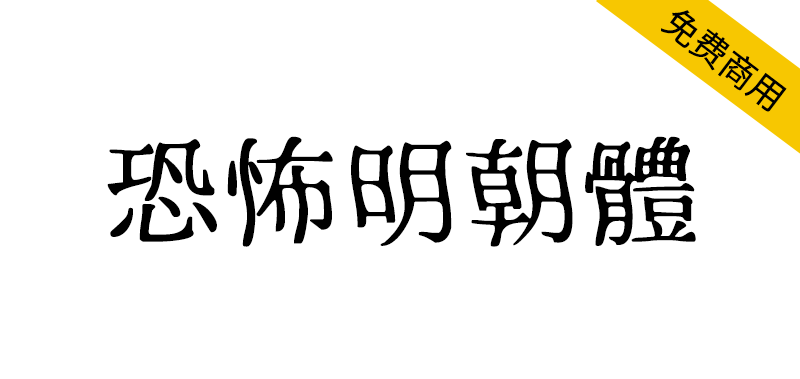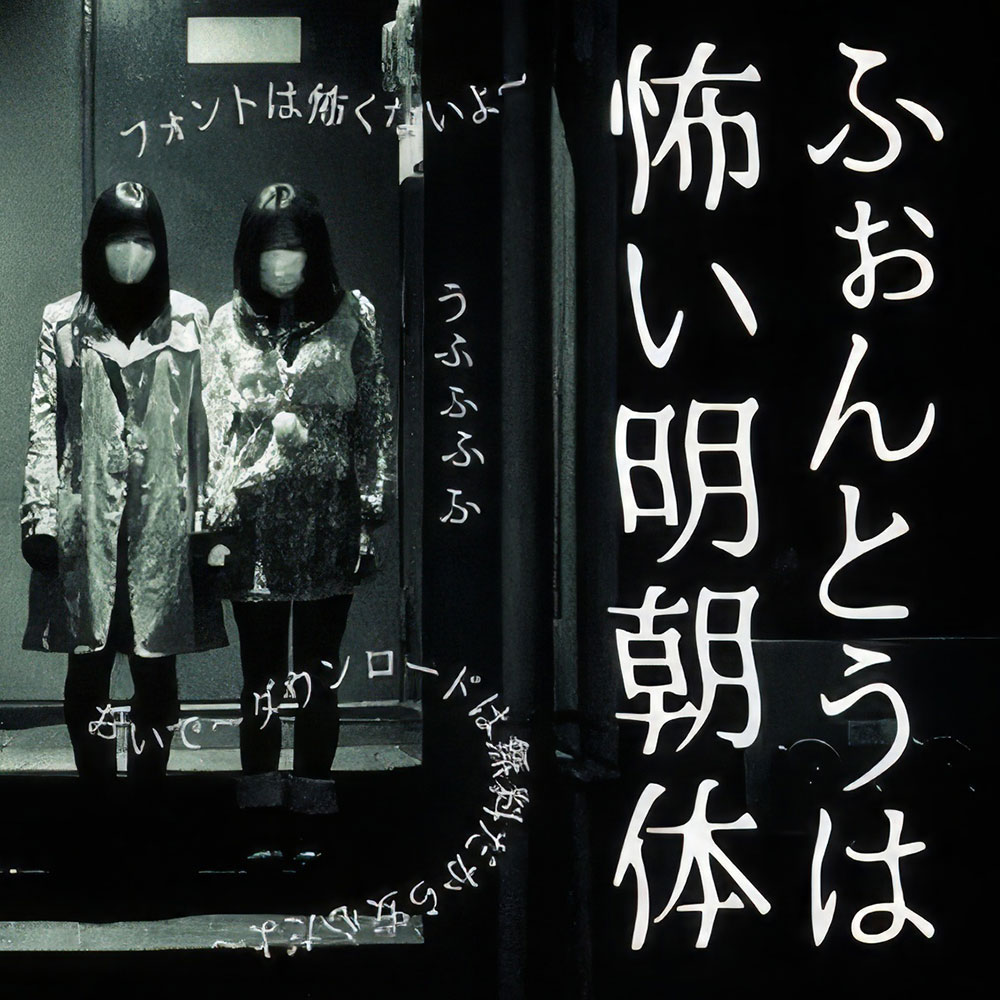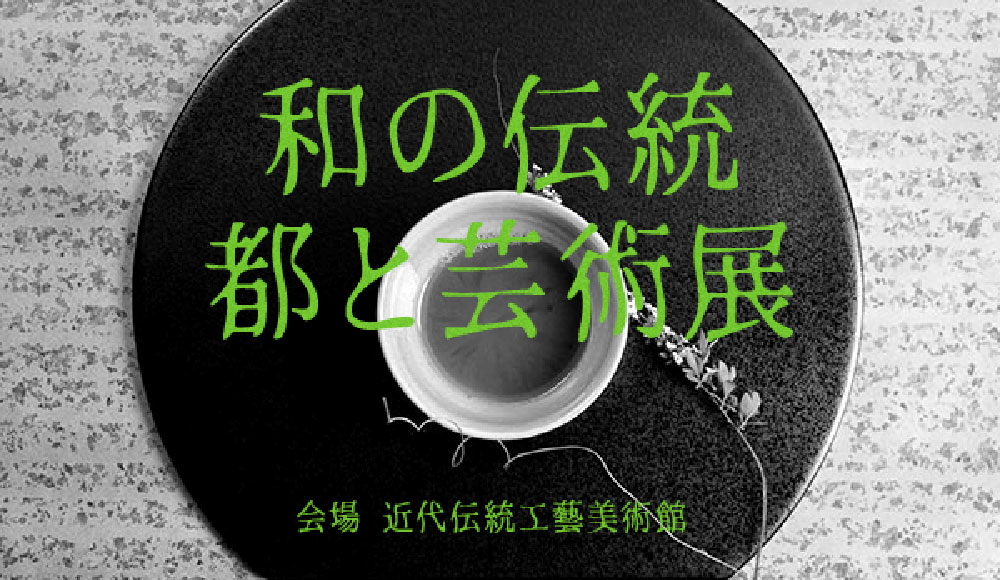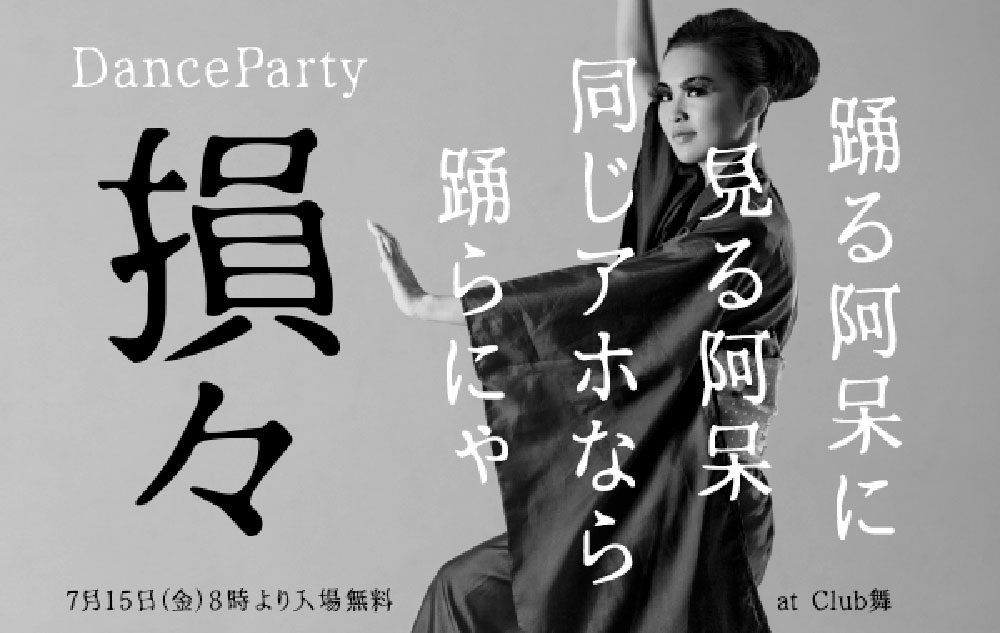
恐怖明朝体(ふぉんとうは怖い明朝体)是一款支持免费商用的日文字体,包含有一些汉字字符集,很适合用于LOGO设计、标题文字和各类醒目排版。其独特的颤抖笔触和略微扭曲的造型,营造出诡异而奇妙的感觉。虽然设计灵感源自典型的日本恐怖电影和惊悚小说,但也可将其视为一种柔和风格的特殊字体。
フリーフォントのふぉんとうは怖い明朝体は無料でダウンロードできる書体です。また商用・非商用問わず使用可能なので、安心してダウンロードして下さい。ロゴデザインやタイトルロゴ、見出し向けの漢字も含まれる日本語フリーフォント。ゆらゆらと揺れるような、少し崩れた印象の世にも奇妙なフォントです。典型的な日本のホラー映画・恐怖小説をイメージしていますがこのフォントをホラーと見るか、柔らかい印象と見るかはあなた次第です。